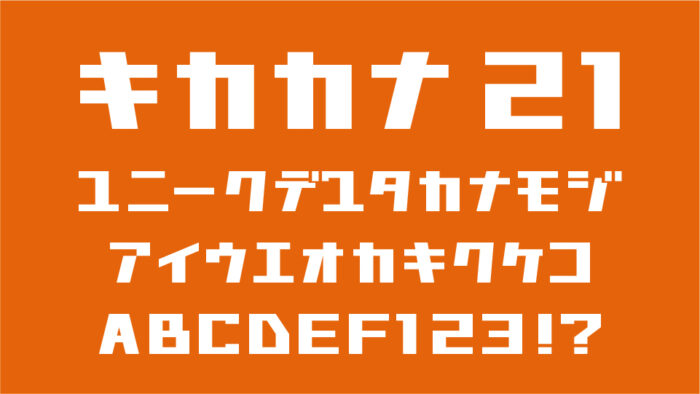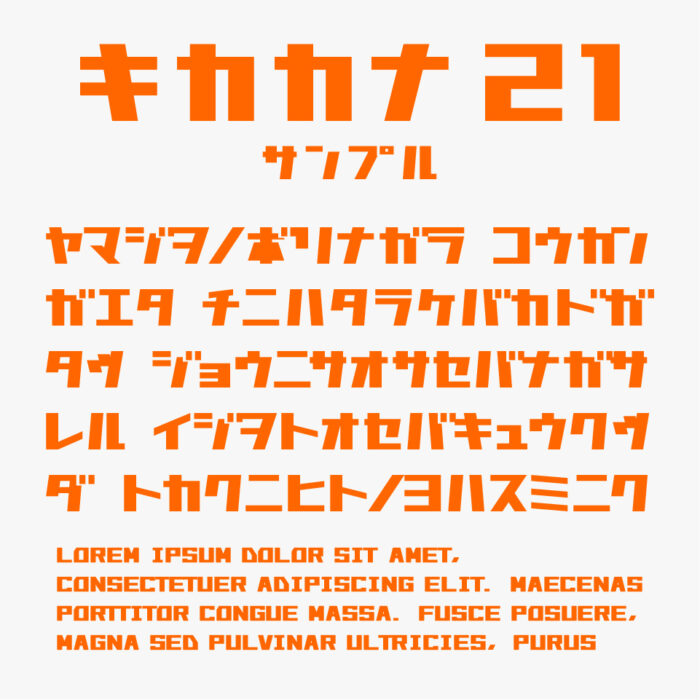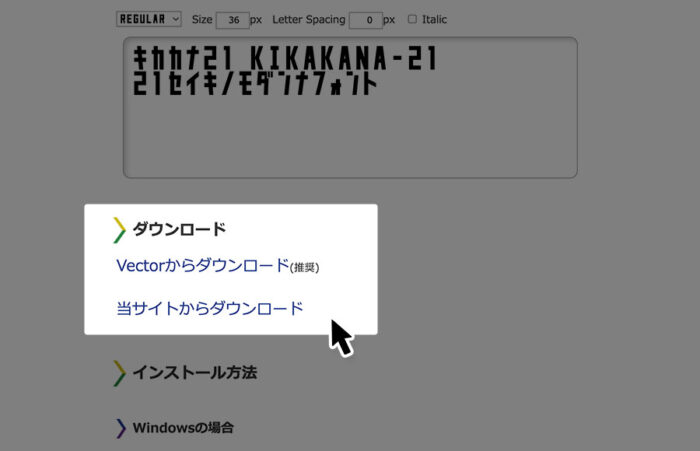
キカカナ21
キカカナ21フォントは、縦2×横1の比率で、直線を組み合わせてデザインされた太字カタカナフォントです。
直線的でシャープな構成により、近未来的な雰囲気があり、テクノロジーやロボティクスを感じるかっこいいデザインです。カタカナと英数字の高さを揃えた設計で、和文と欧文が自然に混在できる点も特長的です。